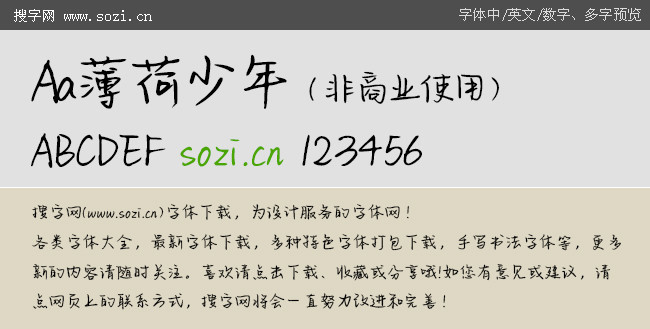
Aa薄荷少年(非商業(yè)使用)
搜字網(wǎng)給大家提供一款A(yù)a薄荷少年(非商業(yè)使用)中文字體下載,該字體是一款手寫中文字體,這款字體端莊,書寫簡潔大方,適合包裝設(shè)計、書裝設(shè)計、海報設(shè)計等應(yīng)用(此字體為個人非商用版,商用可以聯(lián)系QQ:1006760504)。